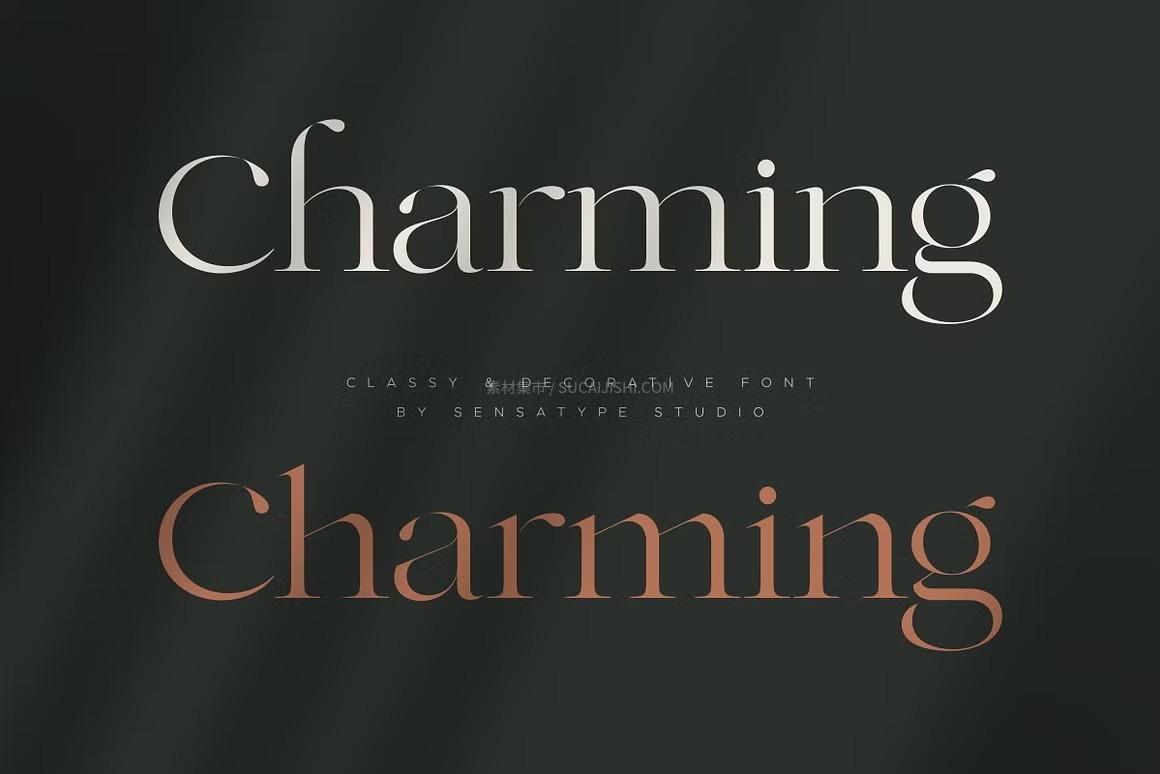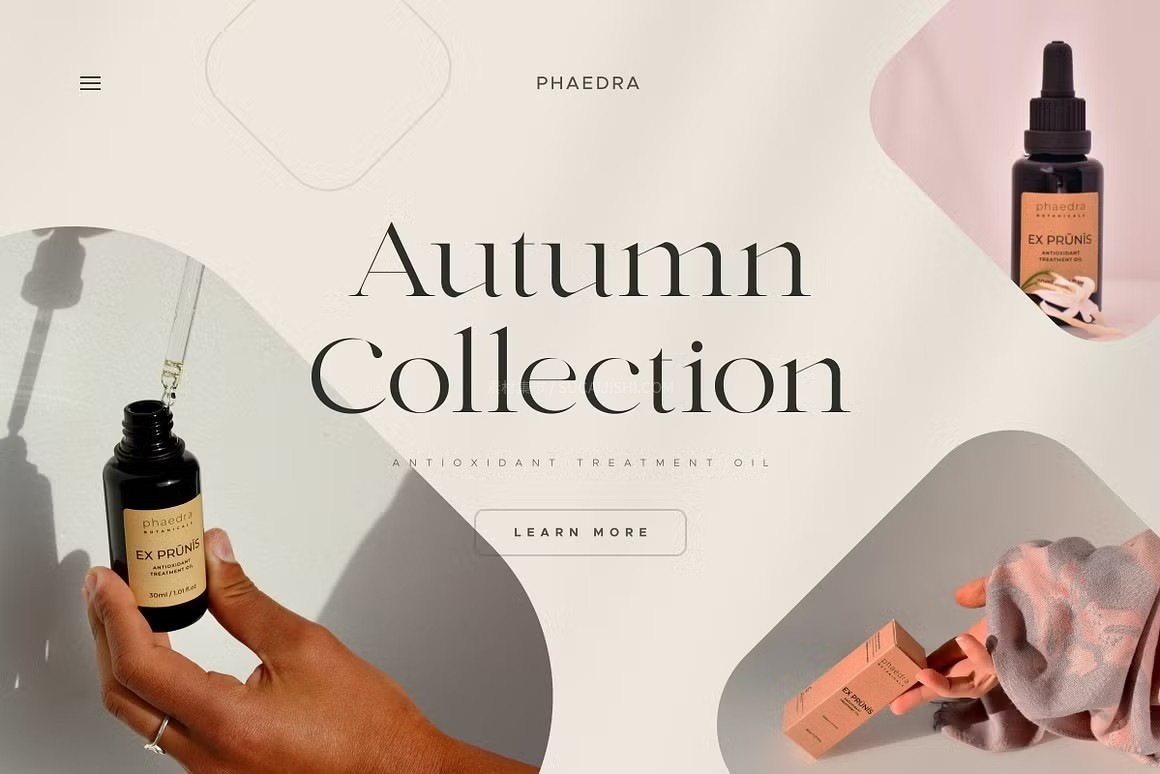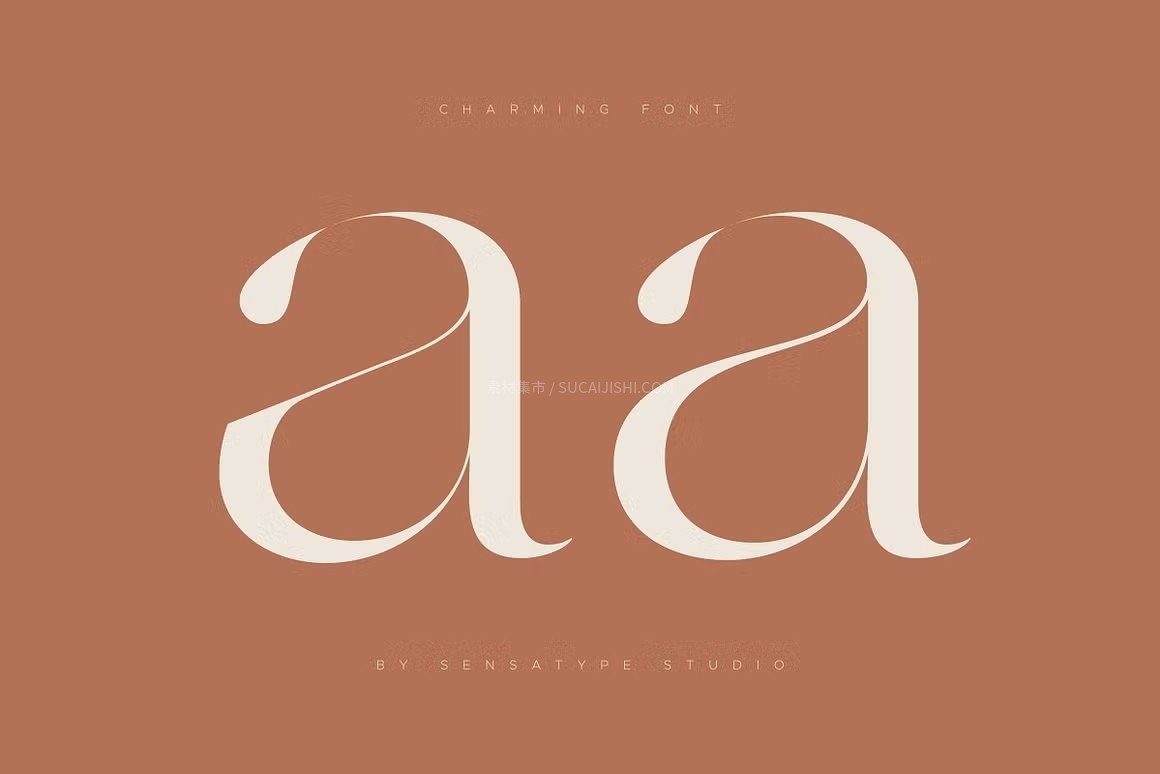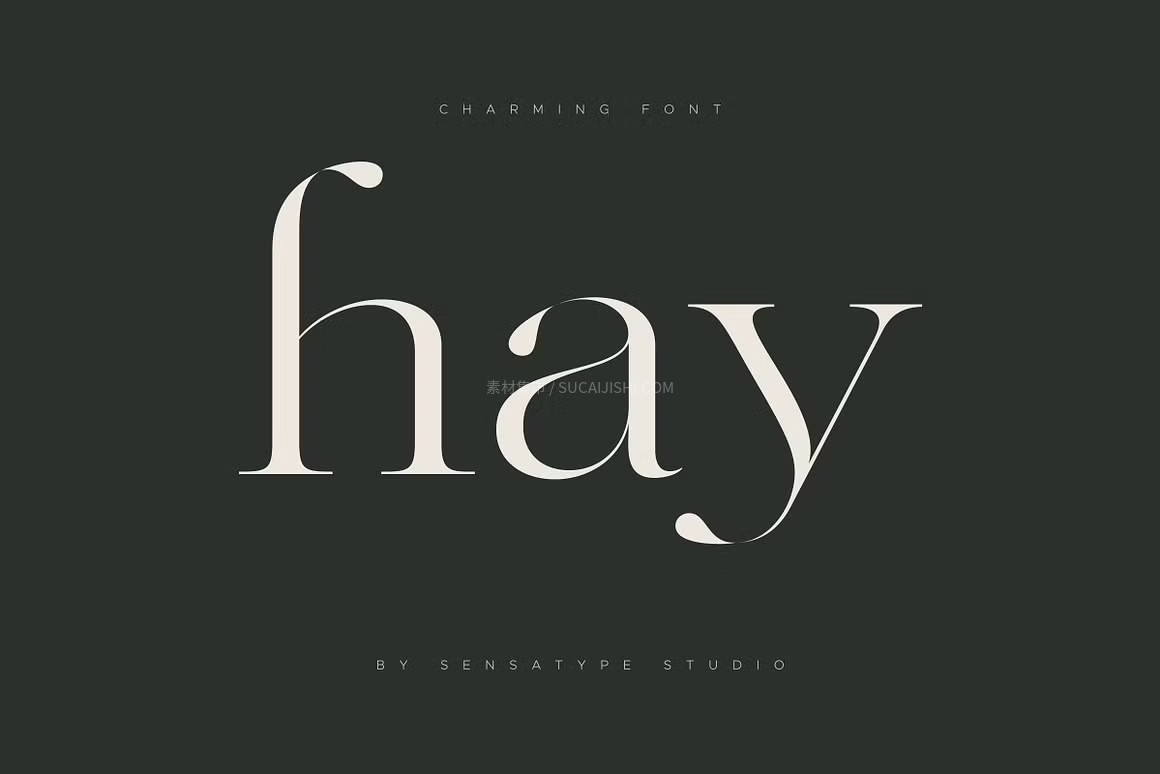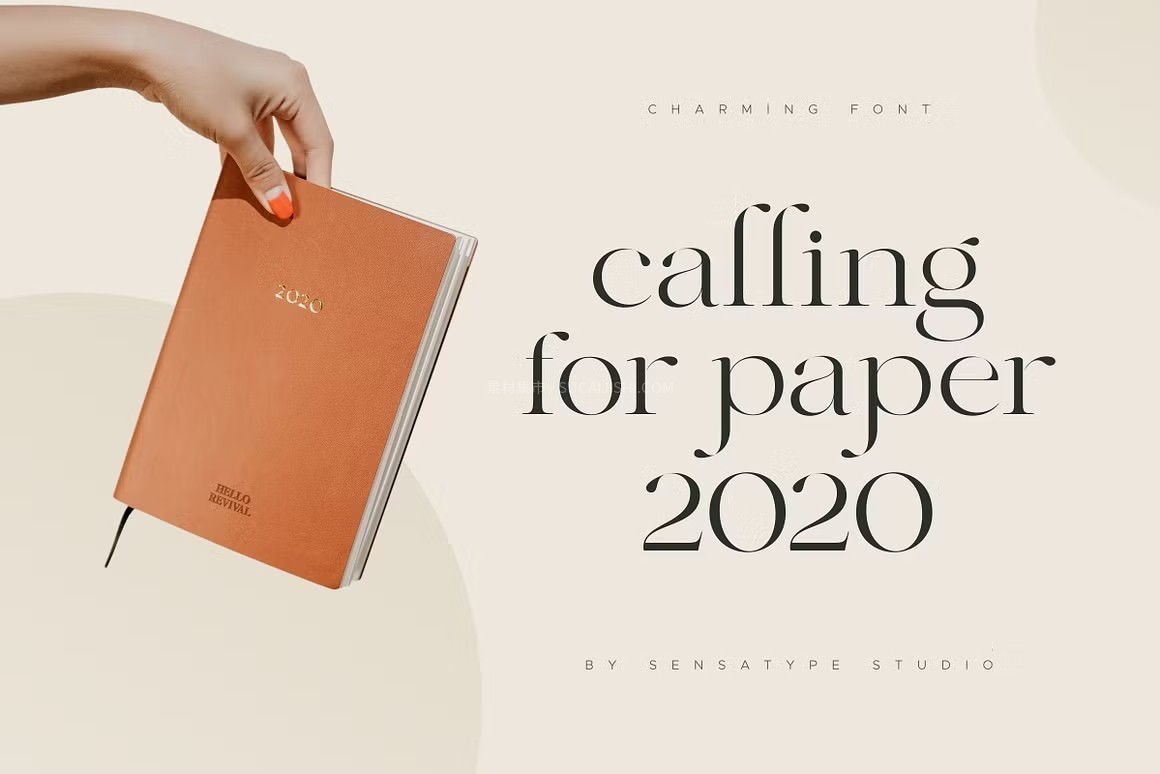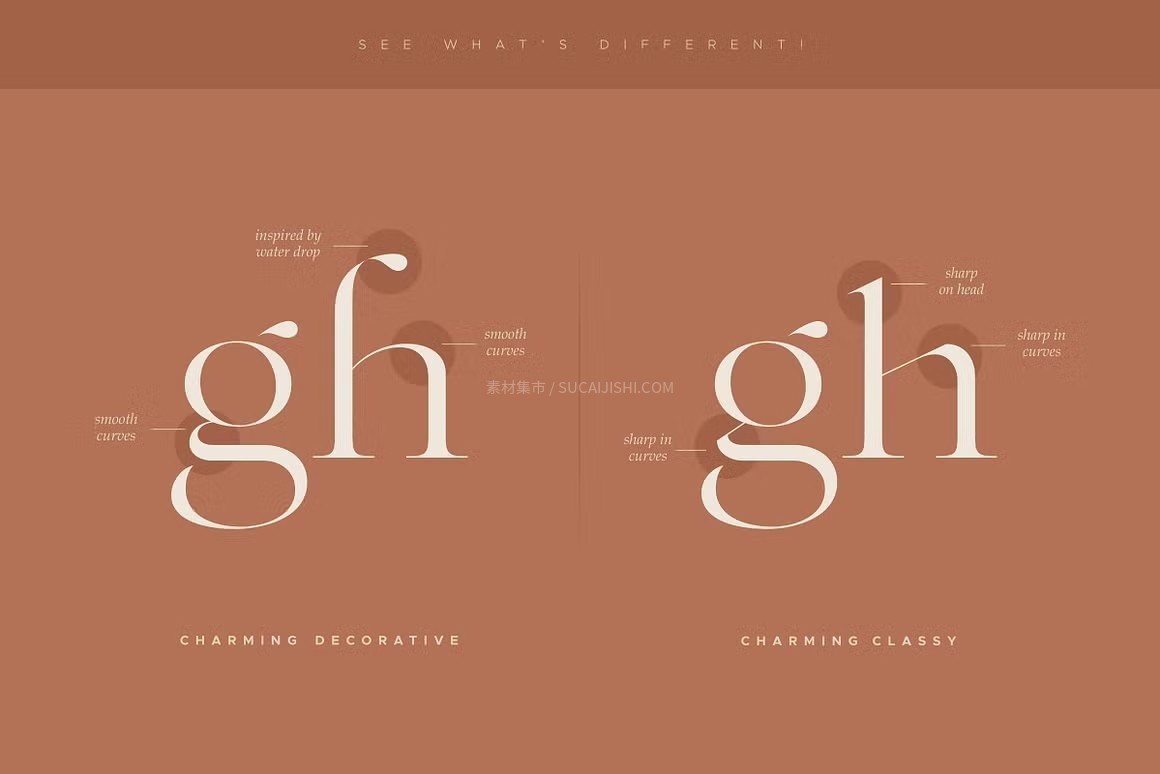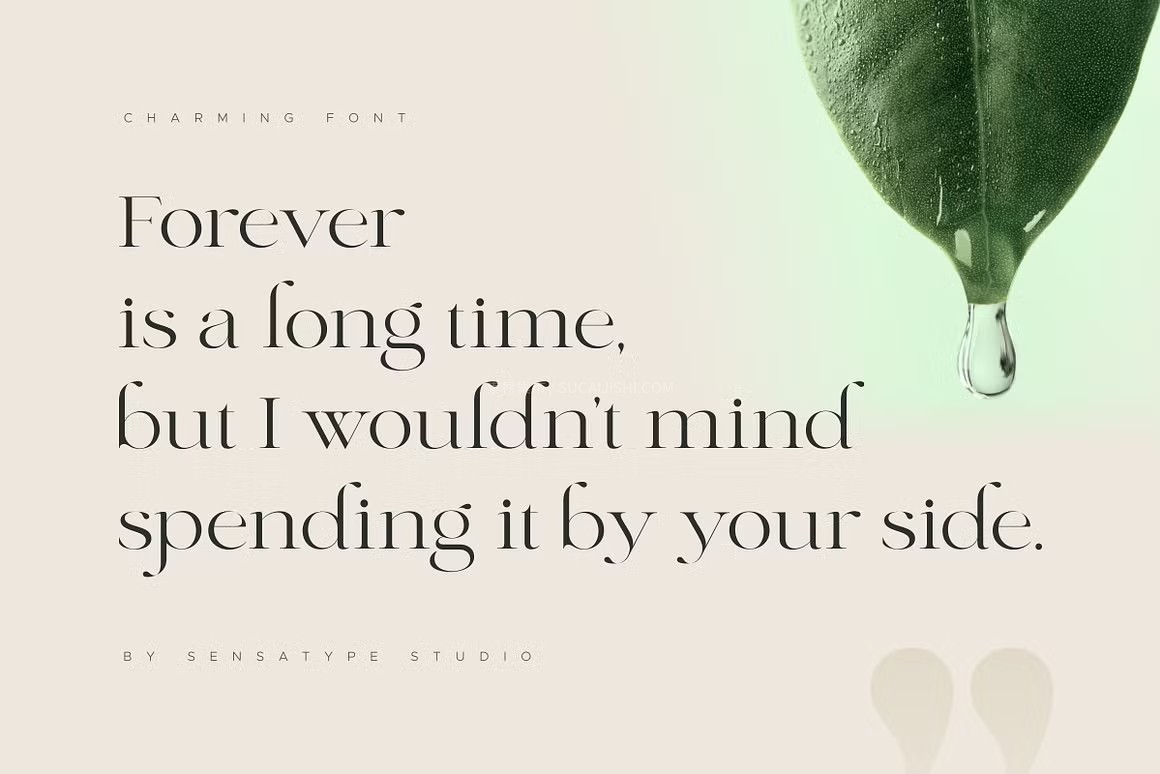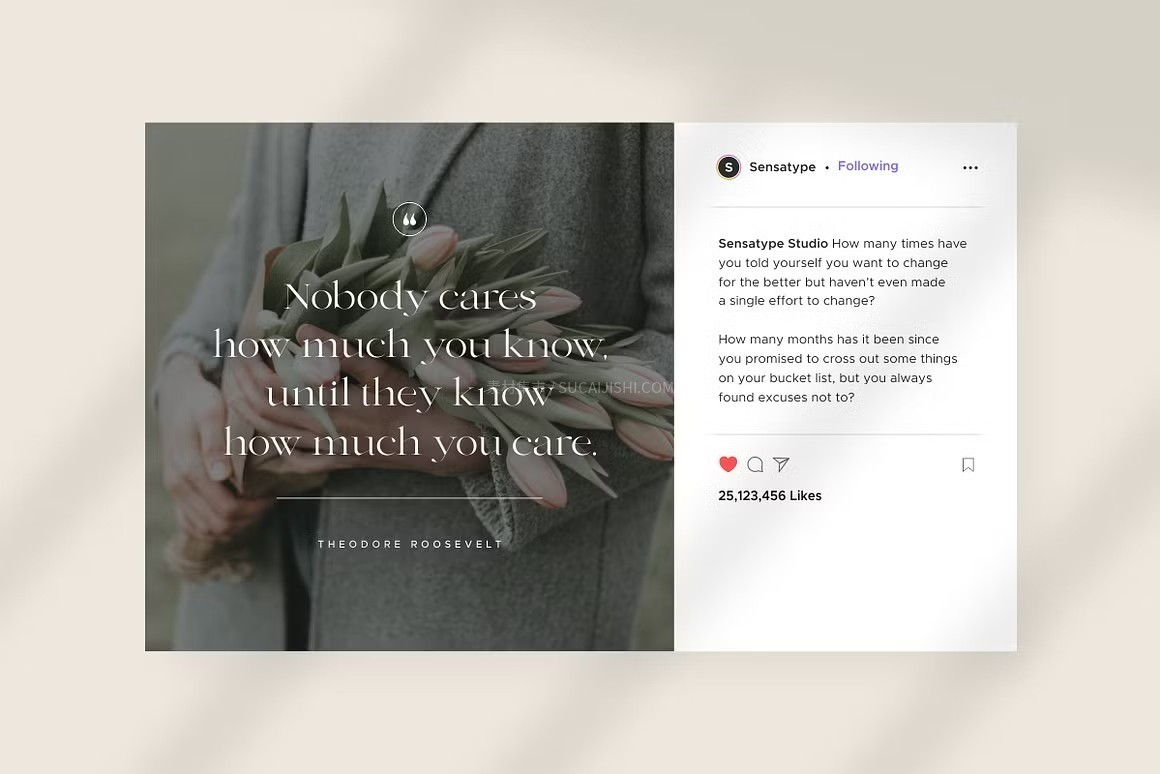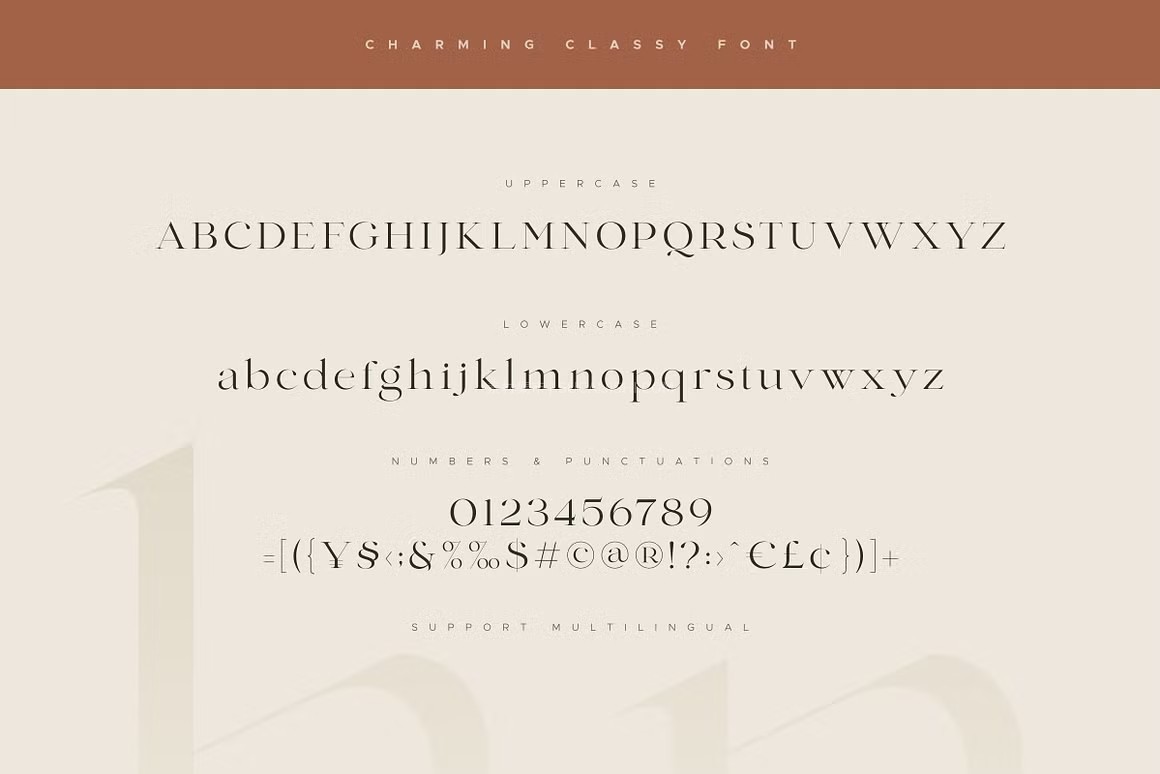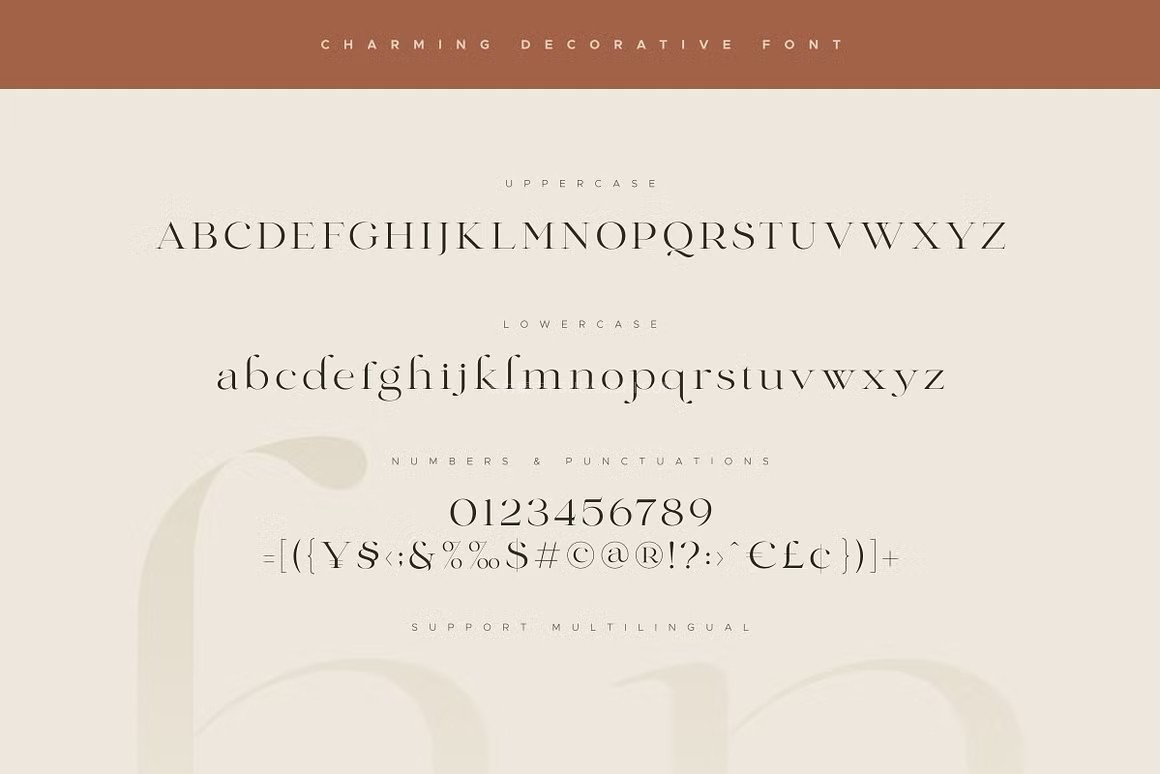
Charming 优雅贵气品牌字体
Charming 是一款兼具卓越功能性与极高美学价值的优雅装饰性英文字体。本款字体由资深商业平面设计师汲取一线实战经验倾力开发,旨在完美平衡“古典优雅气质”与“现代商业排版需求”。适用高端品牌视觉识别系统(VI)设计、企业与产品 Logo 定制、奢侈品及高端零售包装、精美画册与高档杂志排版、商业广告主视觉标题、高级定制物料(如发布会邀请函、VIP名片)等